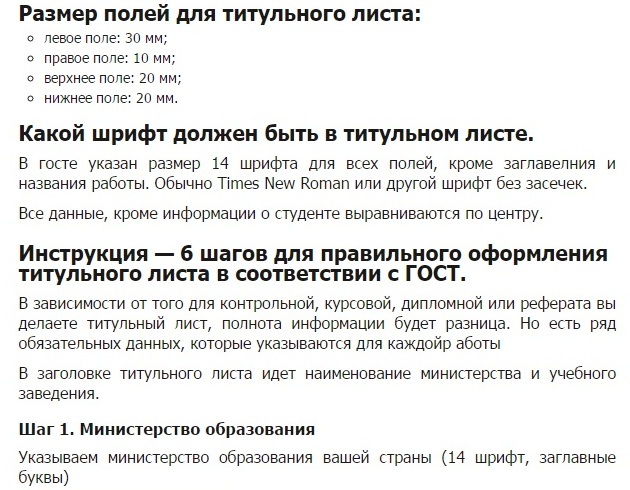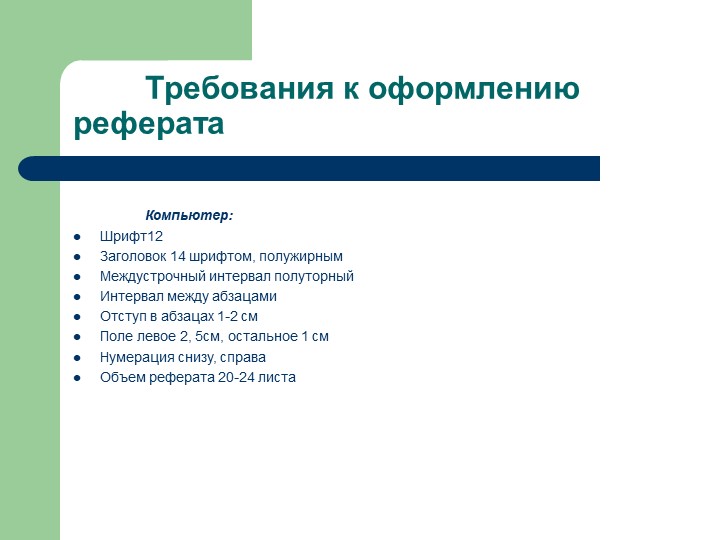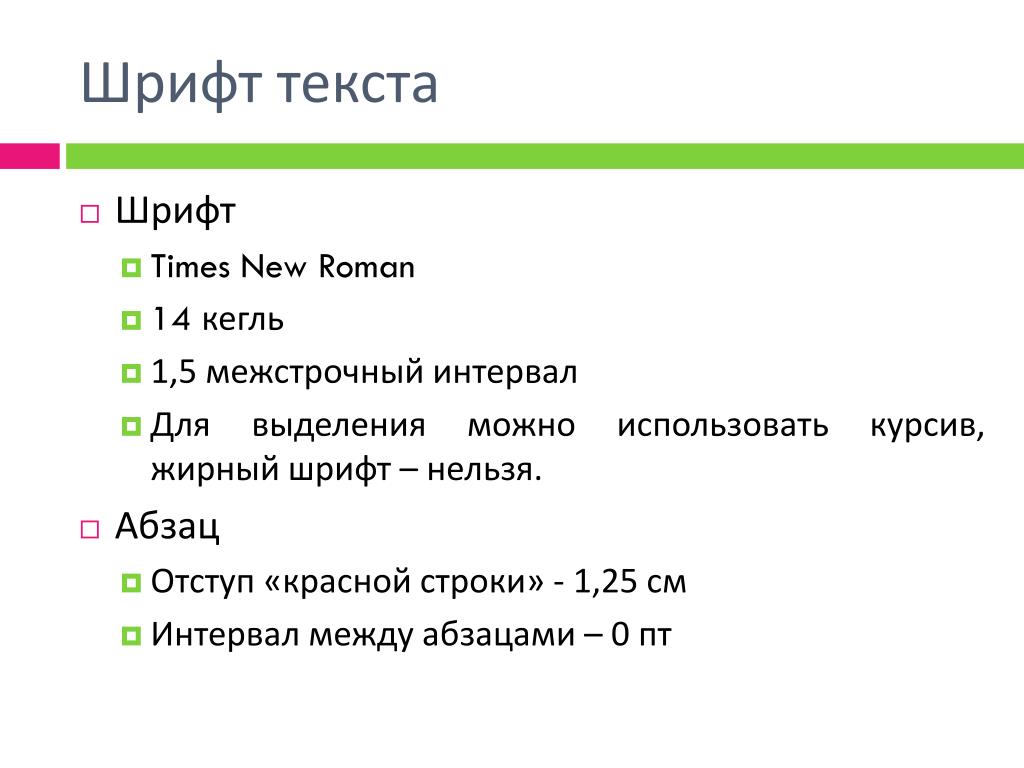
Оформление реферата по ГОСТу 2018 года
Оформление реферата по ГОСТу 2018 года – это очень важный завершающий штрих в работе над этим видом студенческого исследования. Как учесть все нюансы, чтобы получить хорошую оценку, мы рассмотрим в данной статье. Главное правило, которое следует запомнить каждому учащемуся – в оформительской деятельности важно следовать отдельным шаблонам относительно титульного листа, списка литературы, сносок и т.д. (обо всех этих моментах речь идет в других статьях на нашем ресурсе). Организация научной работы согласно всем требованиям ведет к успешной защите и получению высокой оценки.
Оформление реферата по ГОСТу 2018 года: на что обращать внимание в первую очередь?
Чтобы текст на странице выглядел естественно, и при брошюровании часть напечатанного не была утеряна, необходимо соблюдать поля:
- слева – 3 см;
- справа – 1 см;
- сверху и снизу – по 2 см.
Эти параметры можно установить в функциях текстового редактора.
Дальше следует обратить внимание на междустрочный интервал. В оформлении титулки и списка литературы допускается использование одинарного интервала, в остальных же частях – исключительно полуторный. Между двумя заголовками (первого и второго уровней) необходимо оставить пустую строку, между заголовком и текстом – две.
По ходу текста нужно использовать логически завершенные части – абзацы. Каждый абзац начинают с отступа 1,25. Оформляя список литературы и прописывая названия глав (подглав) отступ для абзаца не оставляется.
Применяют в рефератах шрифт типа Times New Roman 14-й кегль. В принципе, допустимо, но не желательно использовать другие шрифты в подобном виде работы. Причина – в том, что во всех компьютерных программах именно Times распознается без искажений, чего нельзя сказать о том же Arial или Calibri.
Основные заголовки, обозначающие названия разделов работы, размещают в верхних строках листа с выравниванием по центру.
Их набирают прописными буквами и выделяют полужирным начертанием.
В конце названия точки не ставятся. Недопустимы также подчеркивание, переносы, сокращения и использование цветных шрифтов (впрочем, это касается всего текста – он должен быть строго черного цвета).
Нумеруют реферат, начиная с третьей страницы, введения. Цифры (арабские) проставляются по центру верхнего или нижнего колонтитула. Без номера оставляют (но при этом учитывают в общую нумерацию) титульный лист и оглавление.
Оформление реферата по ГОСТу 2018 – детали
Оформление реферата по ГОСТу 2018 года невозможно без учета мелких деталей – сносок, списка литературы и т.д.
В частности, сноски должны сопровождать каждую цитату, используемую в тексте. Сноски необходимо заключать в квадратные скобки, обозначая номер источника в списке литературы и номер страницы, откуда взят цитируемый фрагмент. Например, [4; с.12], значит, что использован отрывок из книги под номером 4 из библиографического списка, со страницы 12.
Книги, законодательные акты, периодические издания, электронные ресурсы в списке литературы оформляются с расстановкой по алфавиту (какие нюансы существуют в этом вопросе, мы рассматривали в отдельной статье). Используют литературу, которой не более 5 лет (если работа пишется не по истории).
Объем каждого структурного элемента также регламентируется гостовскими предписаниями:
- введение – до 2-х страниц;
- основной текст – на него отводится от 12-до 20 страниц. Но количество может варьироваться в зависимости от специфики темы, рекомендаций преподавателя по предмету и других факторов;
- выводы – 1-2 листа.
Оформление реферата по ГОСТу 2018 года должно быть произведено на 15-25 страницах печатного текста.
Количество глав в реферате должно определяться самим студентов. Оптимально, если их будет 2-4. Главы (параграфы) в данном виде работы должны быть примерно одинаковыми по объему. Нельзя допускать, чтобы первый раздел, например, состоял из 2-х страниц, а второй – из 10.
Реферат по ГОСТу: стиль и уникальность
Оформление реферата по ГОСТу 2018 года предполагает, что работа должна быть написана четким лаконичным научным стилем с использованием нужной терминологии. Предпочтение следует отдавать безналичным предложениям.
Если реферат претендует на высокую оценку, нельзя забывать о таком важном параметре, как уникальность. При условии активного использования цитат уникальность текста по программе «Адвего Плагиатус» должна быть не менее 55%. Если цитаты не используются или используются мало – не ниже 80%.